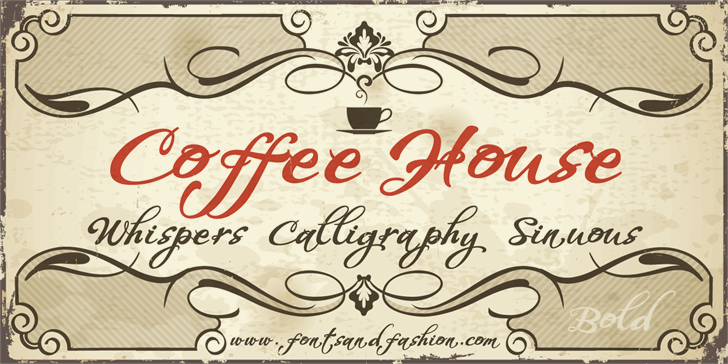
A WHISPERS CALLIGRAPHY font oferece uma experiência única para quem busca uma mão que se destaca em layouts de escrita aquarelada e letras curvilíneas. Criado pelo designer Hamilton em 2014, este tipo de escrita proporciona um ar delicado e elegante, ideal para criações que desejam transpirar sutilidade e leveza. As linhas suaves e os traços fluidos desta fonte chamigraphia permitem aos criadores expressarem sentimentos sutis através do texto, tornando-a perfeita para aplicação em cartões de aniversário, ilustrações aquareladas ou qualquer projeto onde o cuidado detalhista é valorizado. Este é um excelente exemplo de como uma fonte canônia pode ser usada não apenas para escrita normal, mas também para criar uma atmosfera única e romântica em designs de escrita.